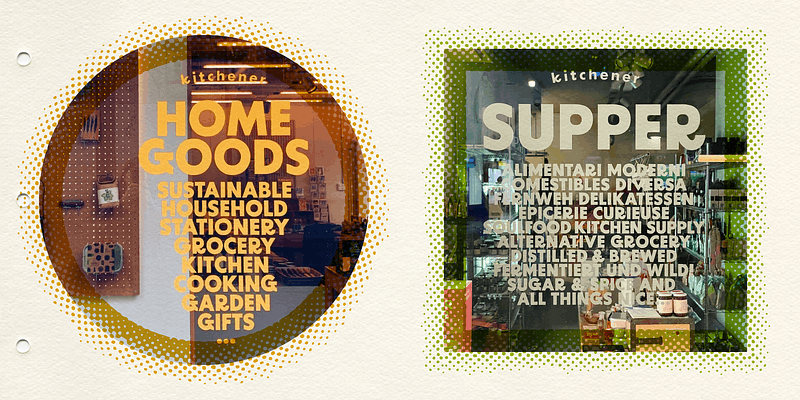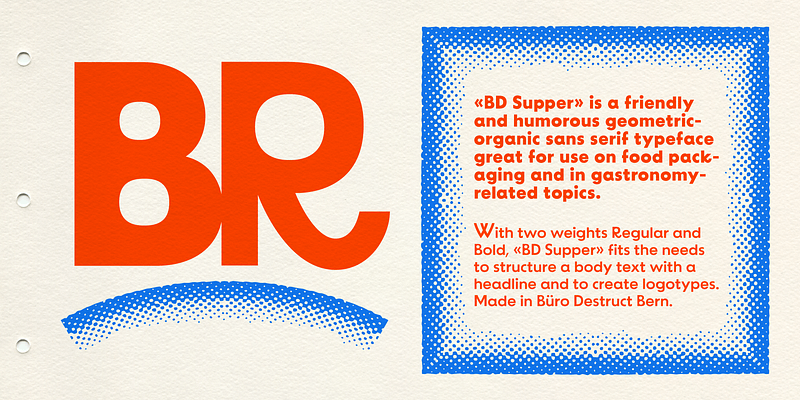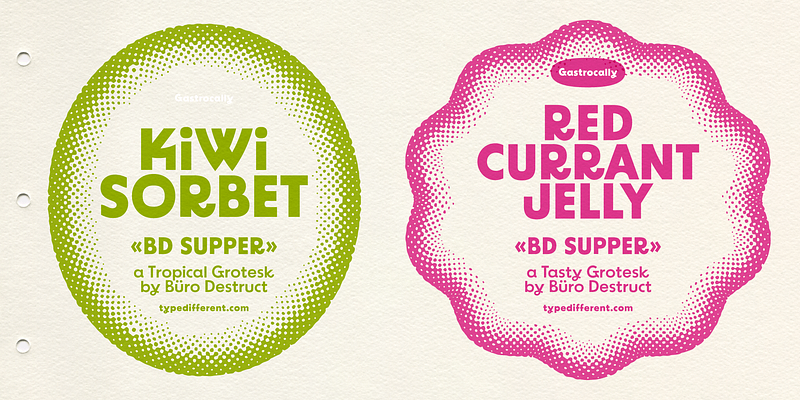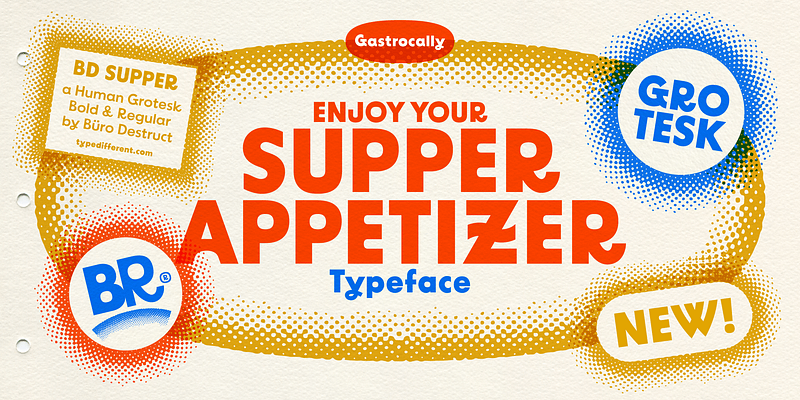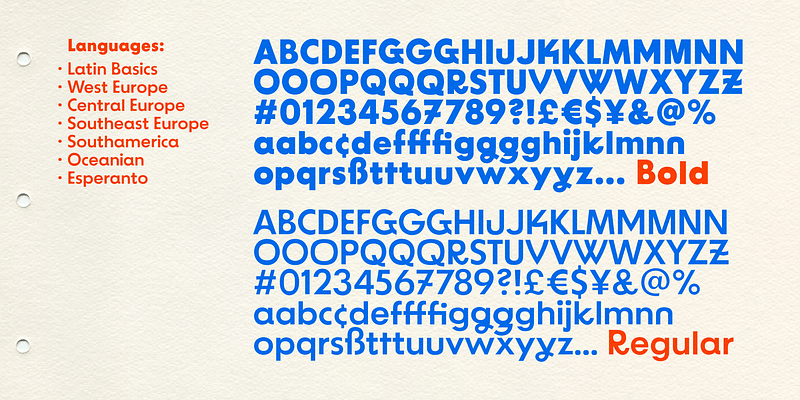
Швейцарская студия графического дизайна Büro Destruct, основанная в 1994 году в Берне HGB Fideljus Бергером и Лоренцом Lopetz Джанфреда. В 1995 году к компании присоединились Марк MB Брюннер и Хайнц H1 Ребер. В течение следующих нескольких лет Büro Destruct выросла во всемирно известную многодисциплинарную студию дизайна. С 1995 года Büro Destruct выпускает свои шрифты в студии под названием Typedifferent.com. Как следует из названия Typedifferent, шрифты Büro Destruct в основном являются дисплейными шрифтами с уникальными характеристиками. Они используются на конвертах для пластинок, в журналах, названиях кинофильмов и телевизионных программ, в каталогах и на веб-сайтах.